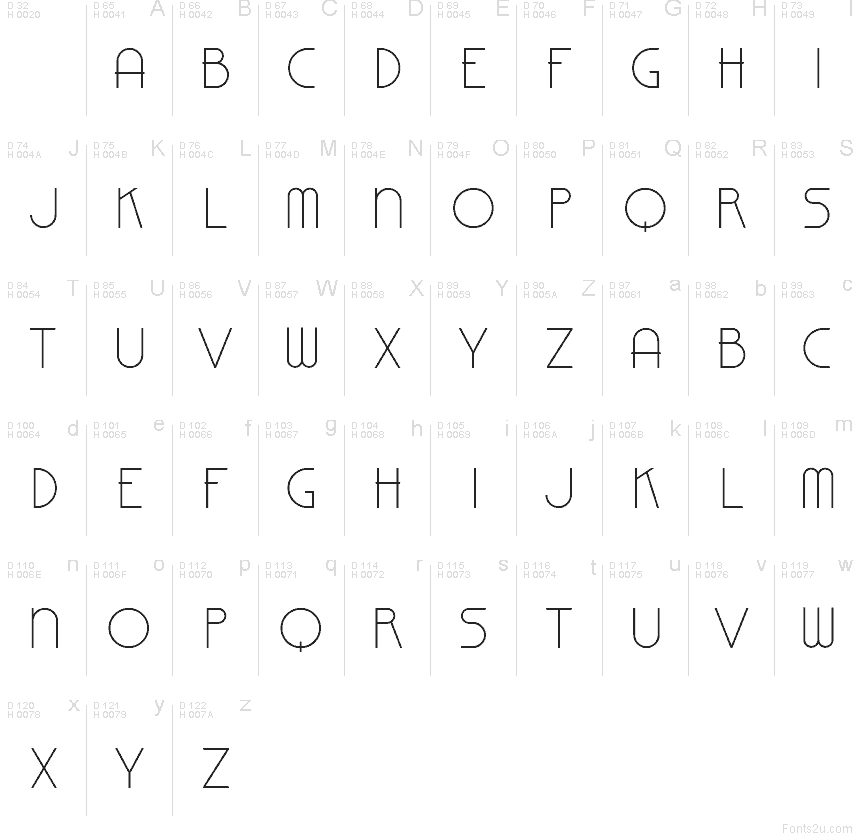
Bauhaus Extravagant od Vladimira Nikolica je bezplatné display písmo inspirované Bauhausem. Tvarosloví tvoří vzpřímené geometrické smyčky, otevřené spodní křivky a dlouhé horizontální příčky, které čistě protínají jednotlivé znaky. Tato opakující se konstrukce dodává písmu střídmý architektonický rytmus, ve kterém se zaoblené oblouky a rovné tahy střídají v pravidelném tempu, aniž by působily příliš měkce či neformálně.
Písmo je ideální volbou pro plakáty, obaly alb, eventový branding, označení kaváren nebo obalový design, kde hledáte ostrý odkaz na raný modernismus bez zbytečné dekorativnosti. Vzhledem k tomu, že se design drží jasné logiky oblouků a příček, vypadají krátké titulky a loga harmonicky a graficky čistě, i když jsou vysázeny pouze několika velkými slovy.
Bauhaus Extravagant